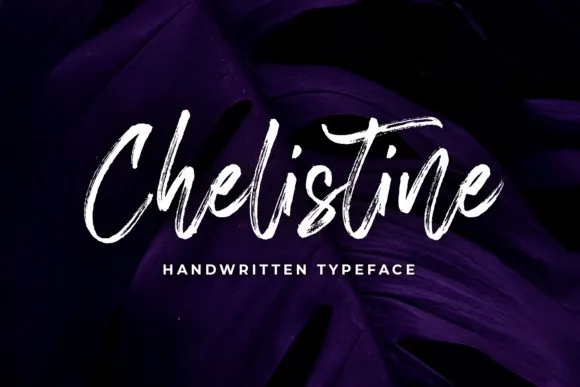
Chelistine Script Font – Download Grátis
A Chelistine Script Font é uma opção incrível para quem busca adicionar um toque especial ao seu projeto visual. Essa fonte script brush foi criada com carinho, cada caractere sendo cuidadosamente pintado de forma perfeita. Ela traz formas curvas fluidas que não deixam a desejar em termos de elegância e modernidade. Esta opção ideal para diversos projetos como cartões de casamento, redes sociais, logotipos e criação de marcas. Além disso, combina muito bem com vários tipos de fontes serifadas. Seja para criar uma identidade visual única ou adicionar detalhes a um projeto gráfico, essa fonte é perfeita. Faça do seu trabalho algo especial com a Chelistine Script Font.